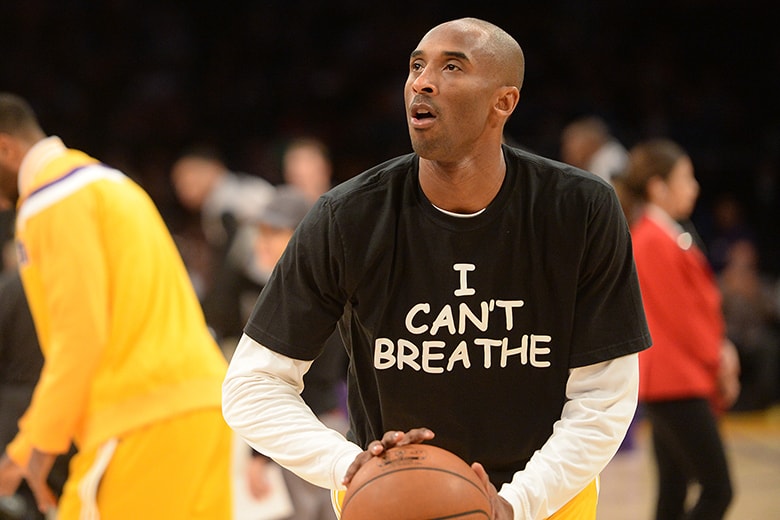
NBA 球星穿上「I Can't Breathe」T-Shirt 抗议近期种族歧视事件
为了声援被纽约白人警察锁喉致死的黑人小贩 Eric Garner,最近 NBA 赛场上出现了多名球星身穿抗议 T-Shirt 的情形。据悉 Eric Garner 在生前最后一句话是「I Can’t
为了声援被纽约白人警察锁喉致死的黑人小贩 Eric Garner,最近 NBA 赛场上出现了多名球星身穿抗议 T-Shirt 的情形。据悉 Eric Garner 在生前最后一句话是「I Can’t Breathe」,因此 Derrick Rose, LeBron James, Kobe Bryant 和 Deron Williams 等球星纷纷穿上了印有这句话的黑色 T-Shirt 现身 NBA 赛场,从而表达自己对于种族歧视事件的抗议。这本是一件表达民主权益的好事,不过却因为 T-Shirt 上所采用的 Comic Sans 字体而在网络上备受争议。事实上这款诞生于 1994 年的漫画风格字体被誉为「全球最不受欢迎字体」,甚至是唯一一款在全球范围内遭到图形设计师公开抵制的字体。